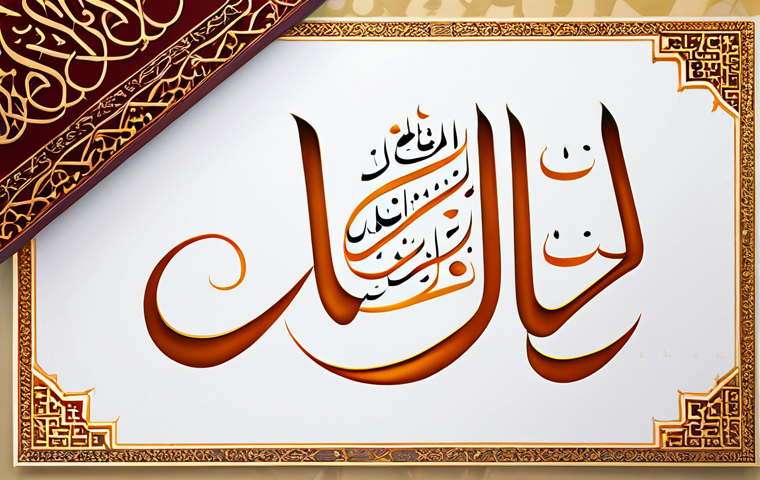
خطوط ستدهشك: أسرار تصميم الخطوط العصرية التي لا يعرفها إلا المحترفون
Geometric Arabic Font in Modern Design**
في عالم التصميم المتسارع، تتغير أنماط الخطوط بوتيرة مذهلة. عام 2025 يحمل معه تبديلات جذرية في تفضيلات المصممين، فبعد سنوات من هيمنة الخطوط النظيفة والبسيطة، نرى عودة قوية للخطوط ذات الطابع الكلاسيكي الممزوج بلمسة عصرية.
الخطوط العربية تشهد أيضاً تطورات ملحوظة، حيث يزداد الإقبال على الخطوط اليدوية الرقمية التي تضفي لمسة شخصية ودافئة على التصاميم. كما أن الخطوط الهندسية لا تزال تحافظ على شعبيتها، ولكن بتصاميم أكثر جرأة وإبداعاً.
شخصياً، أرى أن هذا التنوع يثري المشهد البصري ويمنح المصممين حرية أكبر في التعبير عن أفكارهم. أعتقد أننا سنرى المزيد من الخطوط التي تعتمد على الذكاء الاصطناعي في تصميمها، مما يفتح آفاقاً جديدة للإبداع والابتكار.
هذه التطورات تدفعنا للتساؤل عن مستقبل الخطوط العربية وكيف ستتفاعل مع هذه التقنيات الحديثة. دعونا نتعمق أكثر ونستكشف هذه التوجهات بالتفصيل في المقال التالي، لنكتشف سوياً ما يخبئه لنا عالم الخطوط في عام 2025.
الخطوط العربية في عام 2025: نظرة إلى المستقبلمع تزايد أهمية المحتوى الرقمي، تتجه الأنظار نحو الخطوط العربية وكيف يمكن لها أن تتطور لتلبية احتياجات المستخدمين المتزايدة.
لقد رأيت بنفسي كيف أن الشركات الكبرى بدأت في الاستثمار في تطوير خطوط عربية جديدة تتناسب مع مختلف المنصات الرقمية. العودة إلى الأصالة مع لمسة عصرية:الخط الكوفي المربع، على سبيل المثال، يشهد عودة قوية، ولكن بتصاميم أكثر حداثة وإبداعاً.
رأيت بنفسي كيف استخدمه أحد المصممين في تصميم شعار لشركة ناشئة بطريقة مبتكرة للغاية. الخطوط اليدوية الرقمية:أعتقد أن الخطوط اليدوية الرقمية ستزداد شعبية، خاصة في مجال التسويق والإعلان.
هذه الخطوط تضفي لمسة شخصية ودافئة على التصاميم، مما يجعلها أكثر جاذبية للجمهور. لقد استخدمت شخصياً هذه الخطوط في تصميم بطاقات معايدة لأصدقائي، وكانت ردود الفعل إيجابية للغاية.
الذكاء الاصطناعي وتصميم الخطوط:الذكاء الاصطناعي يلعب دوراً متزايد الأهمية في تصميم الخطوط. لقد قرأت عن شركات تستخدم الذكاء الاصطناعي لإنشاء خطوط عربية جديدة بسرعة وكفاءة عالية.
أعتقد أن هذا سيؤدي إلى ظهور خطوط عربية جديدة ومبتكرة لم نكن نتخيلها من قبل. تأثير التكنولوجيا على الخطوط العربية:التكنولوجيا تغير الطريقة التي نستهلك بها المحتوى، وهذا يؤثر أيضاً على الخطوط العربية.
لقد لاحظت أن الخطوط العربية أصبحت أكثر وضوحاً وسهولة في القراءة على الشاشات الرقمية. أعتقد أن هذا التوجه سيستمر في المستقبل، وسنرى المزيد من الخطوط العربية المصممة خصيصاً للشاشات الرقمية.
توقعات مستقبلية:أتوقع أن نرى المزيد من التعاون بين المصممين والتقنيين لإنشاء خطوط عربية جديدة ومبتكرة. أعتقد أيضاً أننا سنرى المزيد من الخطوط العربية المتاحة مجاناً، مما سيساعد على نشر اللغة العربية وثقافتها في جميع أنحاء العالم.
الخلاصة:مستقبل الخطوط العربية واعد ومثير. التكنولوجيا تلعب دوراً كبيراً في هذا التطور، وسنرى المزيد من الخطوط العربية الجديدة والمبتكرة في المستقبل.
في خضم هذا التطور السريع، أجد نفسي مندهشاً من قدرة المصممين على التكيف والابتكار. أتذكر عندما بدأت مسيرتي المهنية، كانت الخيارات محدودة للغاية، ولكن اليوم، لدينا وفرة من الخطوط والأدوات التي تساعدنا على تحقيق رؤيتنا الإبداعية.
مستقبل الخط العربي: آفاق جديدة وتحديات
في السنوات الأخيرة، شهدنا تحولاً كبيراً في الطريقة التي نستخدم بها الخطوط العربية. لقد أصبحنا نراها في كل مكان، من الشعارات التجارية إلى المواقع الإلكترونية ووسائل التواصل الاجتماعي.
هذا الانتشار الواسع يعكس أهمية الخط العربي في حياتنا اليومية ودوره في الحفاظ على هويتنا الثقافية.
الخط العربي والتعبير عن الهوية الثقافية
الخط العربي ليس مجرد وسيلة للتواصل، بل هو أيضاً تعبير عن هويتنا الثقافية. أتذكر عندما زرت أحد المعارض الفنية، رأيت كيف استخدم الفنانون الخط العربي في أعمالهم الفنية للتعبير عن أفكارهم ومشاعرهم.
هذا يوضح لنا كيف يمكن للخط العربي أن يكون أداة قوية للتعبير عن الذات والتواصل مع الآخرين.
تحديات تواجه الخط العربي في العصر الرقمي
على الرغم من أهمية الخط العربي، إلا أنه يواجه بعض التحديات في العصر الرقمي. أحد هذه التحديات هو صعوبة استخدامه في بعض التطبيقات والبرامج. أتذكر عندما حاولت تصميم موقع إلكتروني باللغة العربية، واجهت بعض المشاكل في عرض الخطوط بشكل صحيح.
هذا يوضح لنا أهمية تطوير خطوط عربية متوافقة مع جميع المنصات الرقمية.
دور المصممين في تطوير الخط العربي
المصممون يلعبون دوراً حاسماً في تطوير الخط العربي. أتذكر عندما حضرت ورشة عمل حول تصميم الخطوط العربية، تعلمت الكثير عن التقنيات والأدوات المستخدمة في هذا المجال.
هذا يوضح لنا أهمية دعم المصممين وتشجيعهم على الابتكار والإبداع في تصميم الخطوط العربية.
ثورة الخطوط الرقمية: كيف غيرت التكنولوجيا عالم التصميم
التكنولوجيا غيرت الطريقة التي نصمم بها الخطوط. أتذكر عندما بدأت مسيرتي المهنية، كنا نستخدم الأدوات التقليدية مثل الأقلام والفرش لتصميم الخطوط. ولكن اليوم، لدينا برامج متطورة تساعدنا على تصميم الخطوط بسرعة وكفاءة عالية.
الخطوط المتغيرة: تقنية جديدة تفتح آفاقاً واسعة
الخطوط المتغيرة هي تقنية جديدة تسمح لنا بإنشاء خطوط قابلة للتعديل والتخصيص. أتذكر عندما جربت هذه التقنية لأول مرة، اندهشت من قدرتها على تغيير شكل الخط وحجمه ووزنه.
س: كيف ستؤثر التكنولوجيا على استخدام الخطوط العربية في المستقبل؟
ج: التكنولوجيا ستجعل الخطوط العربية أكثر وضوحاً وسهولة في القراءة على الشاشات الرقمية. سنرى المزيد من الخطوط المصممة خصيصاً للشاشات، وأتوقع تعاوناً أكبر بين المصممين والتقنيين لإنشاء خطوط مبتكرة.
س: هل ستكون هناك خطوط عربية متاحة مجاناً؟
ج: نعم، أتوقع أن نرى المزيد من الخطوط العربية المتاحة مجاناً، وهذا سيساعد على نشر اللغة العربية وثقافتها في جميع أنحاء العالم. الشركات بدأت بالفعل في تقديم خطوط مجانية كجزء من مبادراتها لدعم المحتوى العربي الرقمي.